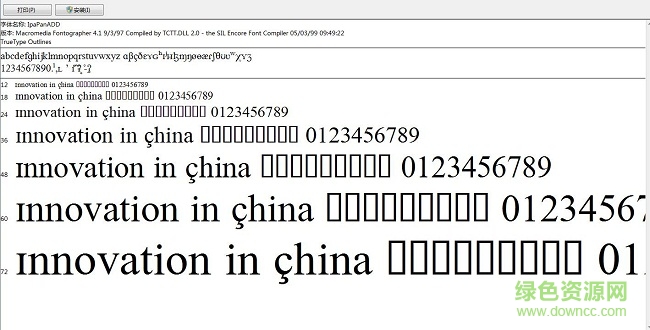
ipapanadd字體是一款ttf格式的國際音標(biāo)字體,支持Windows和Mac系統(tǒng),有些軟件運行需要用到這款字體,如果你的電腦音標(biāo)顯示亂碼的話,可以在本站下載安裝該字體進行修復(fù)!
國際音標(biāo)早期又稱萬國音標(biāo),是一套用來標(biāo)音的系統(tǒng),以拉丁字母為基礎(chǔ),由國際語音學(xué)學(xué)會設(shè)計來作為口語聲音的標(biāo)準(zhǔn)化標(biāo)示方法。
國際音標(biāo)嚴(yán)格規(guī)定以“一符一音”為原則,即“一個音素一個符號,一個符號一個音素”。
此外,在不同的語言中,同一個音有不同的拼法。例如,英語的sh,法語的ch,德語的sch,波蘭語的sz,捷克語的s ,實際上都是國際音標(biāo)的[ʃ]音。